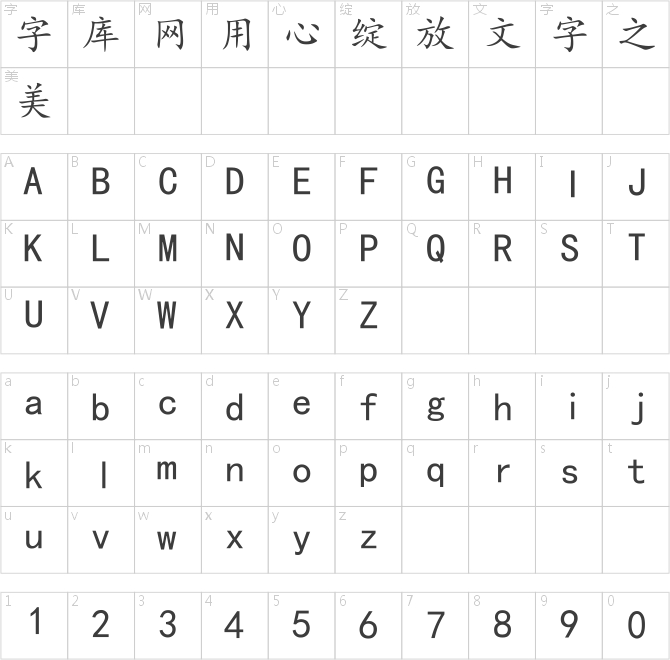
肖氏楷體二簡字 詳情頁
字體名稱: 肖氏楷體二簡字
肖氏楷體二簡字
肖氏楷體二簡字字體下載KaiTiErjian
肖氏楷體二簡字字體KaiTiErjian字庫是一款讓人賞心悅目、百看不厭的中文字體,適合各類廣告和產品包裝設計應用,字體大小11.3MB,格式為ttf字體,上傳用戶是隨緣゜,作者/版權方為肖氏